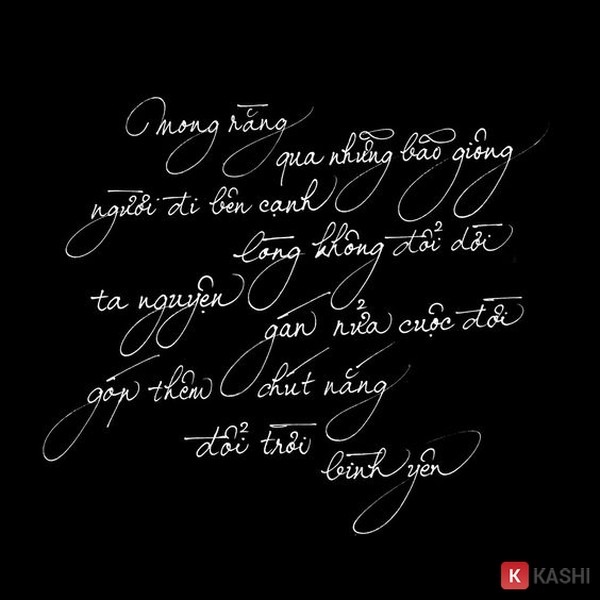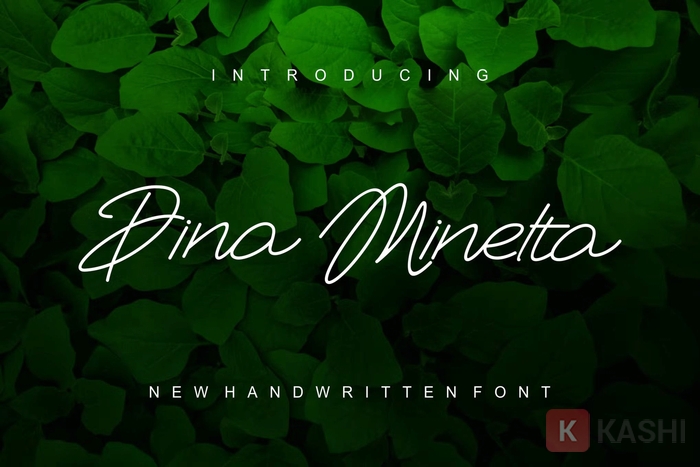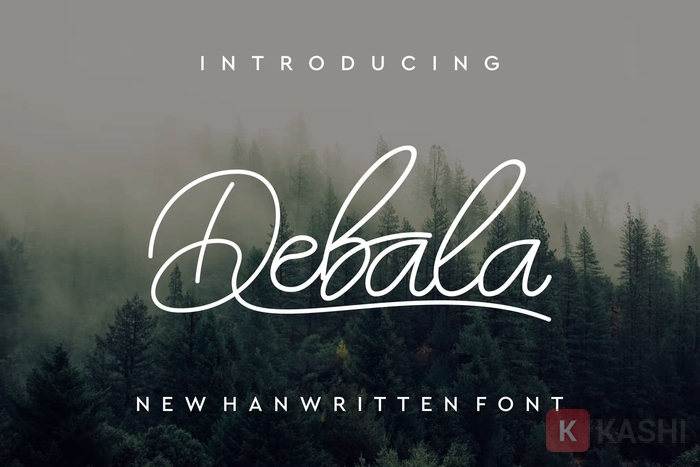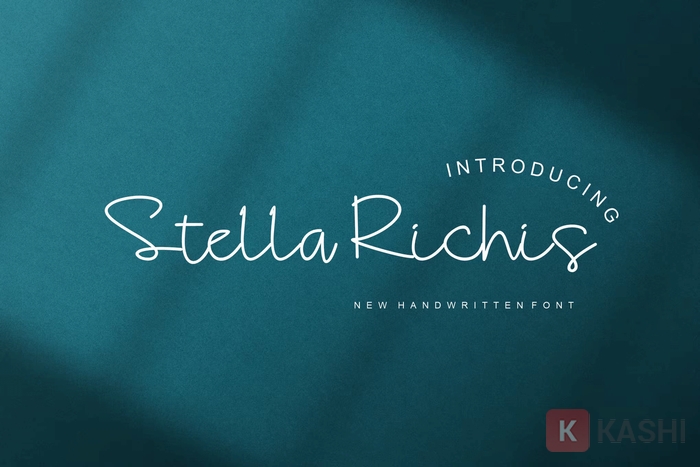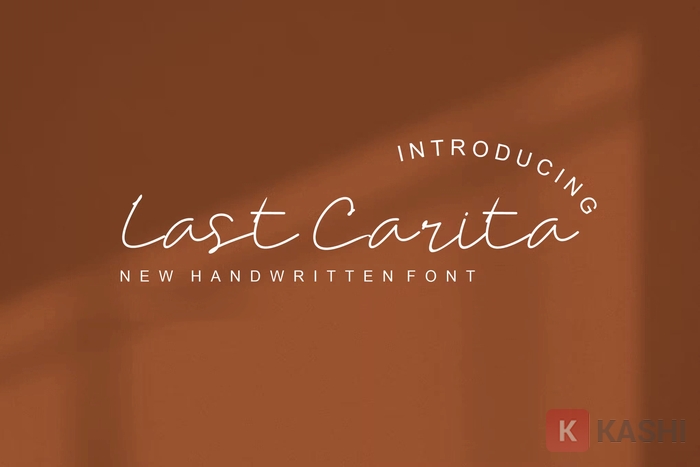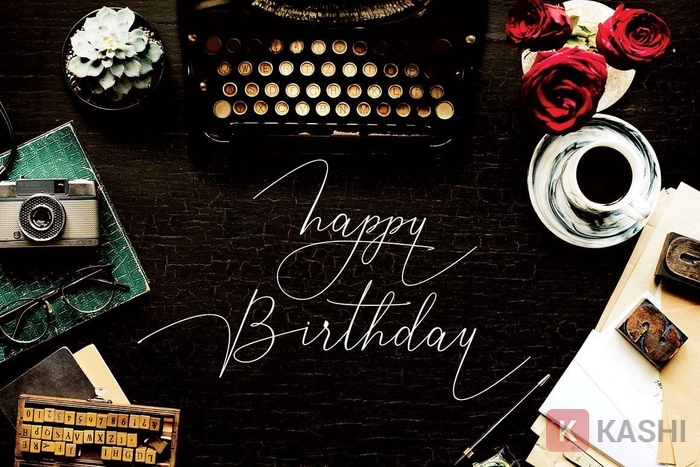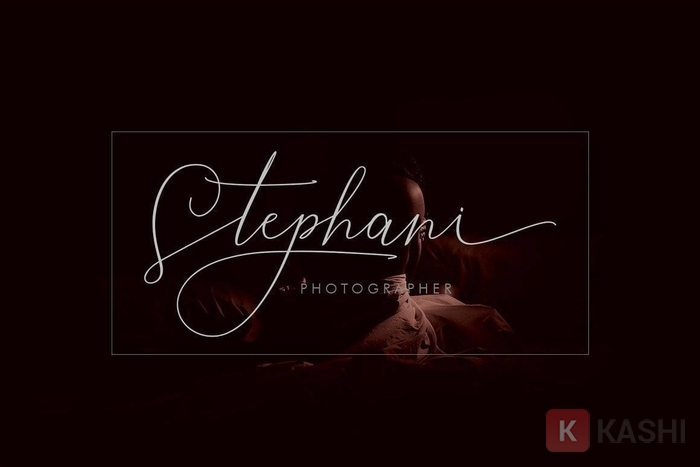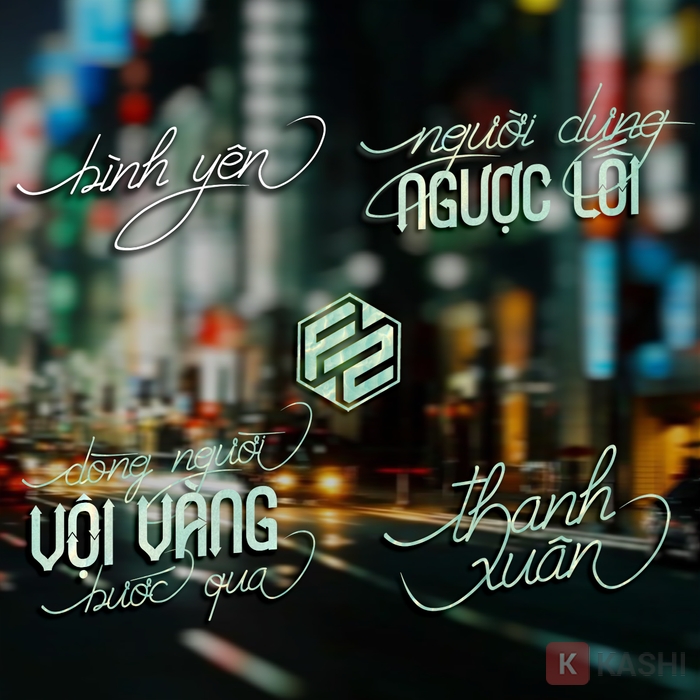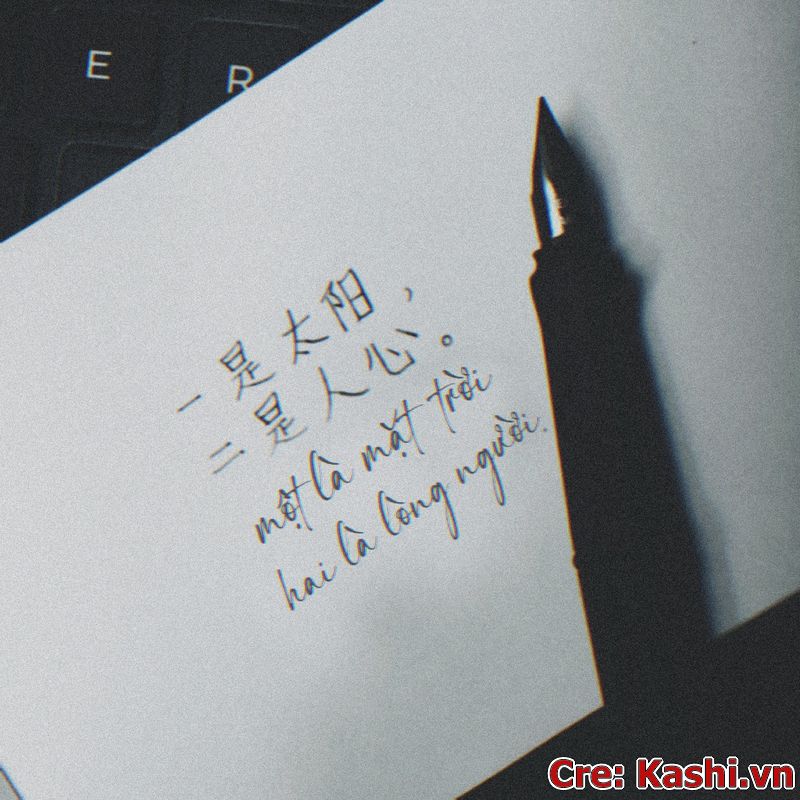
Font Chữ Viết Tay Là Gì?
Font chữ viết tay là tập hợp các font chữ đã được Việt hóa, giúp bạn dễ dàng chèn chữ vào thiết kế đồ họa mà không gặp lỗi hiển thị. Đúng như tên gọi, phông chữ viết tay mô phỏng nét chữ viết tay tự nhiên.
Ví dụ font chữ viết tay
Có rất nhiều bộ font chữ viết tay khác nhau, phù hợp với nhiều phong cách thiết kế. Chúng thường được sử dụng trong logo, tiêu đề, ghi chú, nhưng ít khi dùng cho nội dung văn bản dài. Bạn sẽ tìm thấy nhiều kiểu chữ viết tay với các nét chữ biến tấu, tạo nên sự khác biệt tinh tế.
So với font chữ máy đều đặn, font chữ viết tay mang đến sự phá cách và tự do hơn. Trên thực tế, font chữ viết tay thường dùng trong trang trí hoặc thư pháp vì tính đa dạng và ấn tượng của nó.
Đặc điểmMô tả
Loại FontFont chữ viết tay Việt hóa
Mẫu chữVintage, Calligraphy, nét thanh nét đậm,…
Tính Năng Của Font Chữ Viết Tay
Font chữ viết tay mang nét đẹp thanh lịch, tương tự như font chữ thông thường nhưng cuốn hút và ấn tượng hơn.
Font chữ ký Signature
Chúng được sử dụng như font chữ chính thức, thường thấy trên poster. Mỗi bộ font chữ viết tay đều có tính thẩm mỹ và chức năng riêng biệt, phù hợp với nhiều dự án thiết kế khác nhau.
Bộ Font Chữ Viết Tay Nét Mỏng:
Font chữ viết tay nét mỏng 1
Font chữ viết tay nét mỏng 2
Font chữ viết tay nét mỏng 3
Font chữ viết tay nét mỏng 4
Font chữ viết tay nét mỏng 5
Muốn thiết kế mang đậm dấu ấn cá nhân? Hãy thêm logo và đồ họa, đặc biệt là font chữ viết tay. Font chữ viết tay thường được sử dụng trong thiệp mời, poster hoặc các văn bản cần sự thanh lịch, trang trọng, giảm bớt sự cứng nhắc.
Tổng Hợp Font Chữ Viết Tay Đẹp 2025
Dưới đây là một số bộ font chữ viết tay đẹp nhất 2025:
Font chữ viết tay Duo
Font chữ viết tay Witter 1
Font chữ viết tay Witter 2
Font chữ viết tay Witter 3
Font chữ viết tay Witter 4
Font chữ viết tay Witter 5
Font chữ viết tay Witter 6
Font chữ viết tay Witter 7